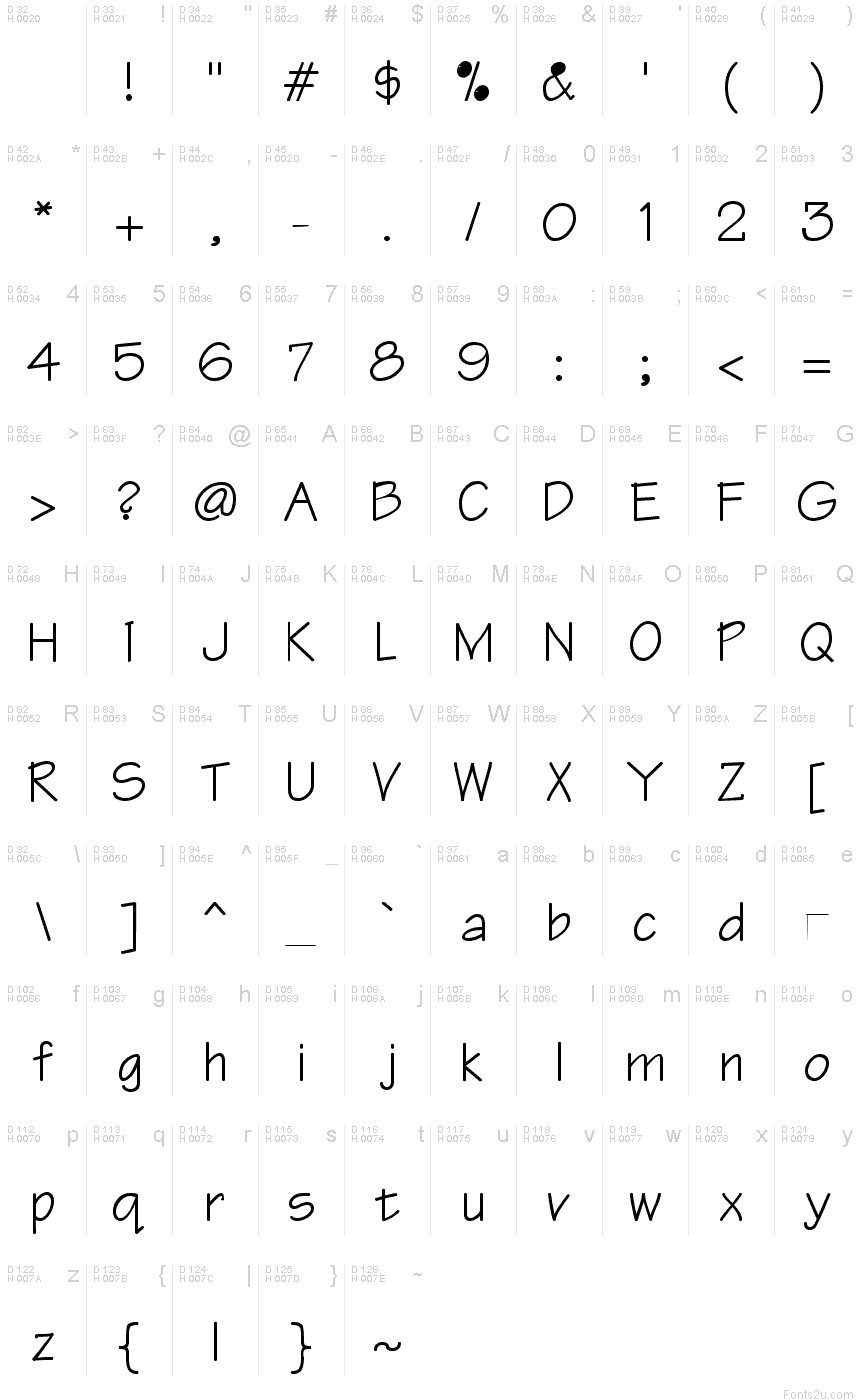
Krój pisma Architect Bold od Hanka Gillette nadaje rodzinie Architect-Bold wyrazisty, techniczny charakter, przypominający pociągnięcia kreślarskim piórem. Geometria jest zdyscyplinowana: ostre kąty, otwarte światło i spokojny rytm, który sprawia, że font wygląda nowocześnie, ale nie chłodno. Architect-Bold Bold to nowoczesny, darmowy font displayowy, dzięki któremu Twój przekaz pozostanie lekki nawet w większych rozmiarach.
Architect Bold doskonale sprawdza się w portfolio architektonicznym, makietach oznakowania, nagłówkach UI, plakatach technicznych, tytułach wystaw, minimalistycznych logotypach oraz księgach znaku wymagających porządku i przejrzystości. Pozwól, by ten darmowy font dominował w średnich i dużych rozmiarach, a w tekście głównym połącz go z cieplejszym bezszeryfowym krojem humanistycznym lub neutralnym szeryfem, aby dodać projektowi kontrastu i wygody.